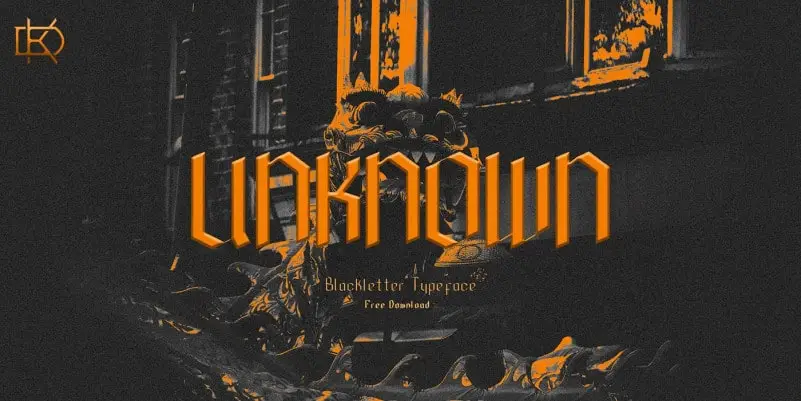
Unknown Display Font – Fonte Grátis
Unknown Display Font
A Aurora é uma fonte de exibição clássica inspirada nos estilos de design dos anos 70. Suas linhas finas e elegantes são perfeitas para projetos que exigem um destaque imediato, como banners sociais, anúncios, desenhos em t-shirt, embalagens, marca, entre outros. Esta fonte é versátil o suficiente para ser usada tanto de forma normal quanto em todas as letras maiúsculas. Seus arredondados e linhas retas criam uma aparência chamativa que se destaca em qualquer projeto, tornando-a uma escolha ótima para ambientes onde você deseja destacar o texto com estilo. Ideal para um design visual impactante, a Aurora é perfeita para projetos de design gráfico atuais e futuros.